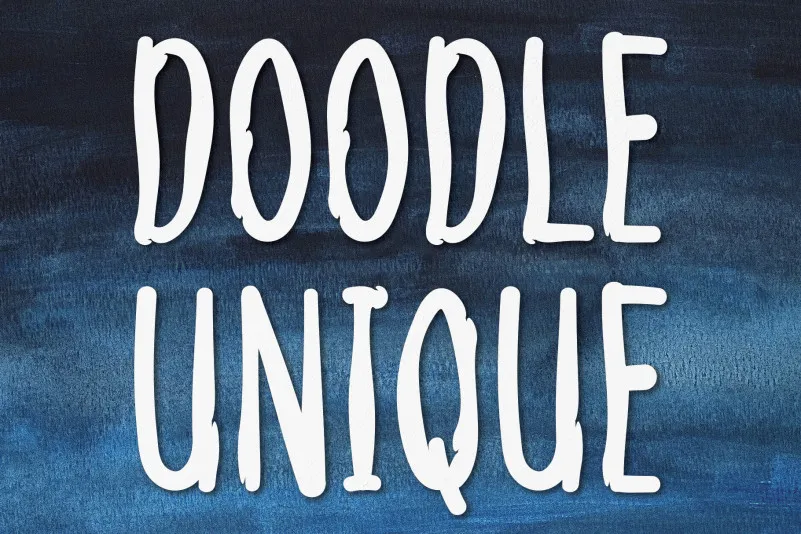
DOODLE UNIQUE Display Font – Download Grátis
A fonte DOODLE UNIQUE Display Font é uma escolha perfeita para quem busca uma experiência visual vibrante e inovadora em seus projetos digitais. Desenhada pelo designer AndiKasStudio, essa fonte de display é ideal para estilos criativos que valorizam a simplicidade e a amabilidade no design. Com letras robustas e de textura grossa, ela convida os designers a explorar um novo nível de expressividade em seus projetos. Seja para criar logomarcas memoráveis ou adicionar personalidade aos elementos de texto, a DOODLE UNIQUE Display Font transformará qualquer projeto em um verdadeiro sucesso visual. Suas linhas desenhadas com um toque irretocável combinam simplicidade e originalidade, oferecendo uma fonte que se destaca entre as demais, tornando-a perfeita para designers buscando estilos únicos e imprimindo sua marca de maneira única no mercado.